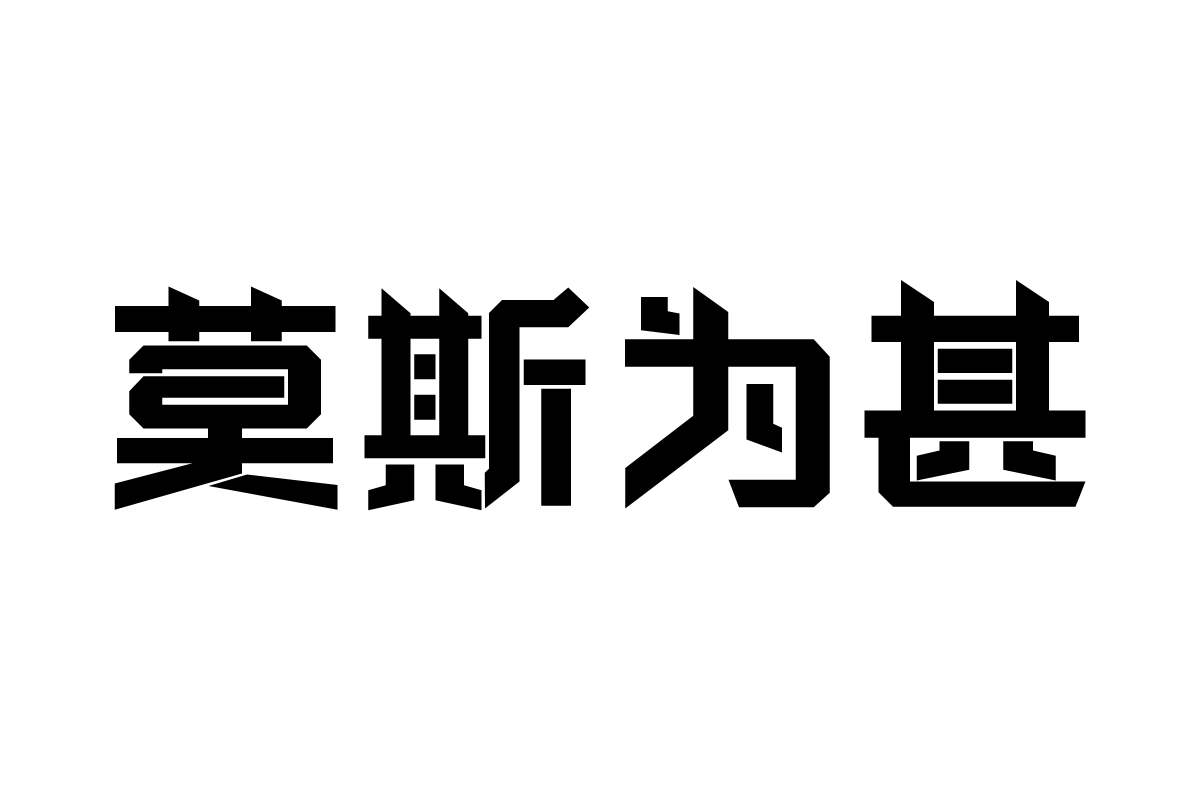
三极芯片体超粗字体是一种用于电子设备和计算机系统中的字体。它具有以下特点:
1. 超粗的字形:这种字体的特点是字形非常粗壮,给人一种强烈的视觉冲击力。这使得它在需要强调或突出显示的文字中非常有用。
2. 高对比度:由于字形粗壮,这种字体在黑白屏幕或低分辨率屏幕上仍然清晰可见。这使得它在电子和计算机系统中非常有用。
3. 可读性:虽然字形粗壮,但这种字体仍具有良好的可读性。它能够清晰地传达信息,即使在小字号下也能保持清晰度。
4. 适应性强:这种字体适用于多种设备和平台,包括桌面计算机、笔记本电脑、平板电脑和智能手机。这使得它在各种不同的应用场景中都非常有用。
总之,三极芯片体超粗字体是一种功能强大且适应性强的字体,非常适合用于电子设备和计算机系统中。